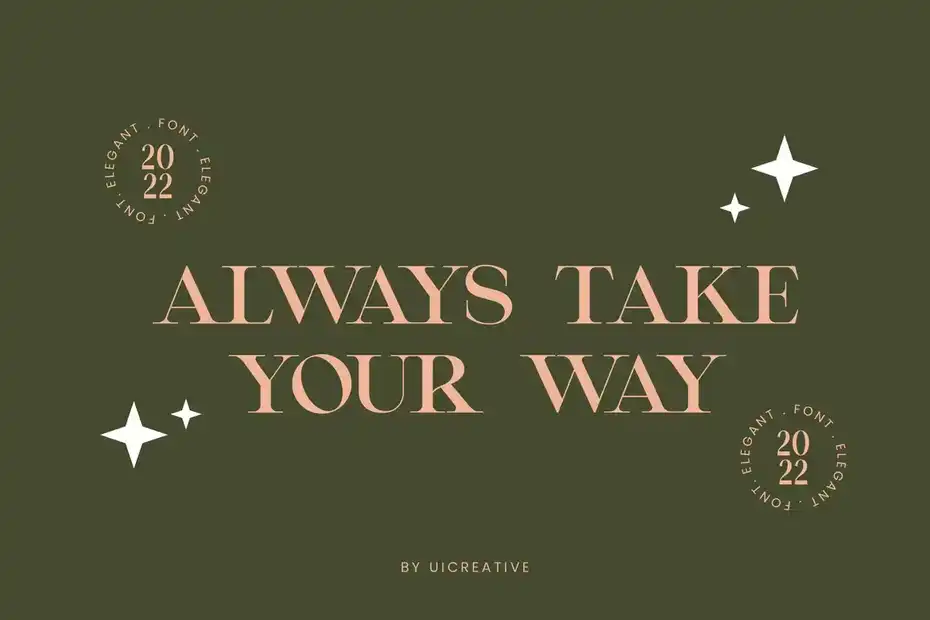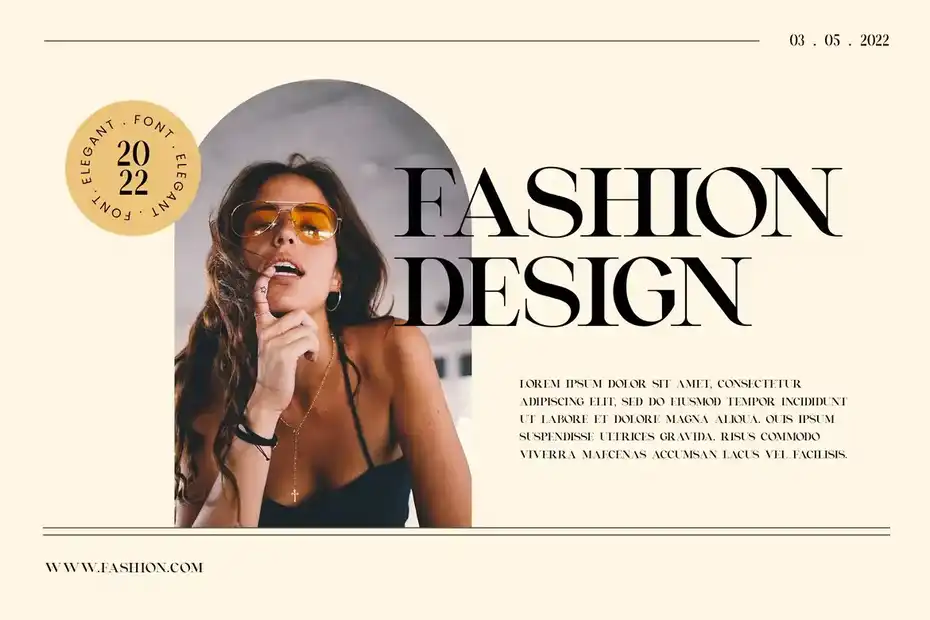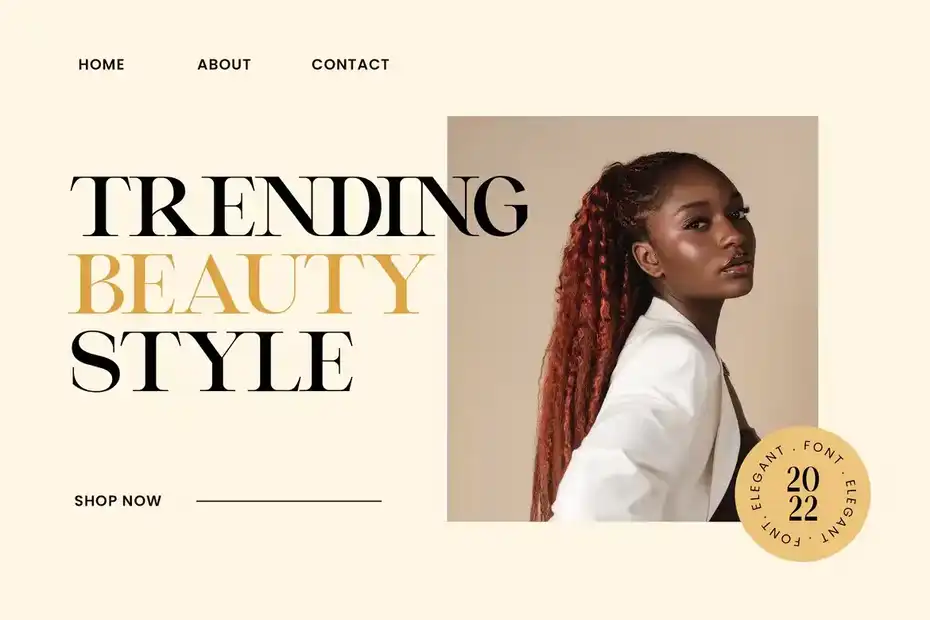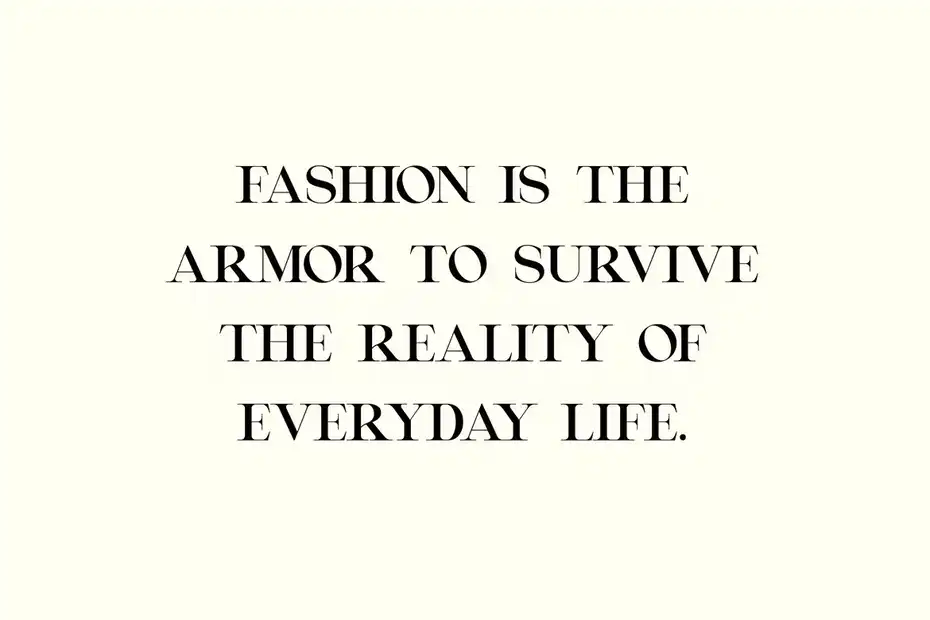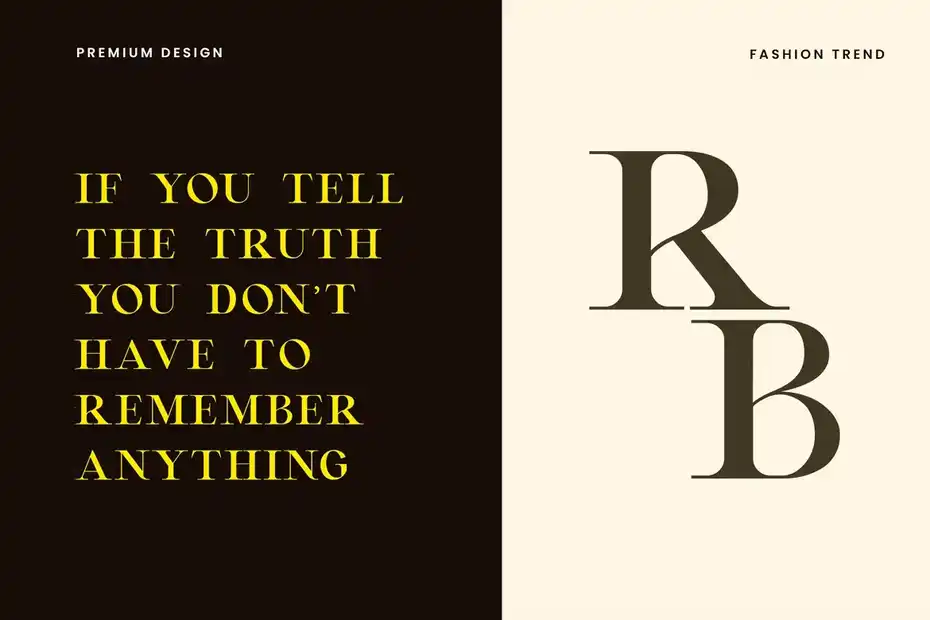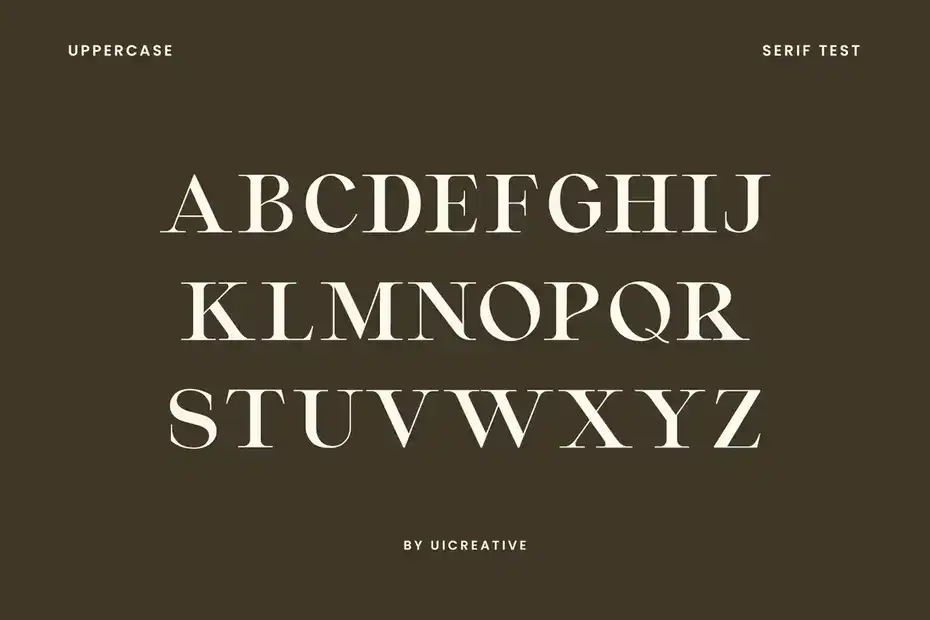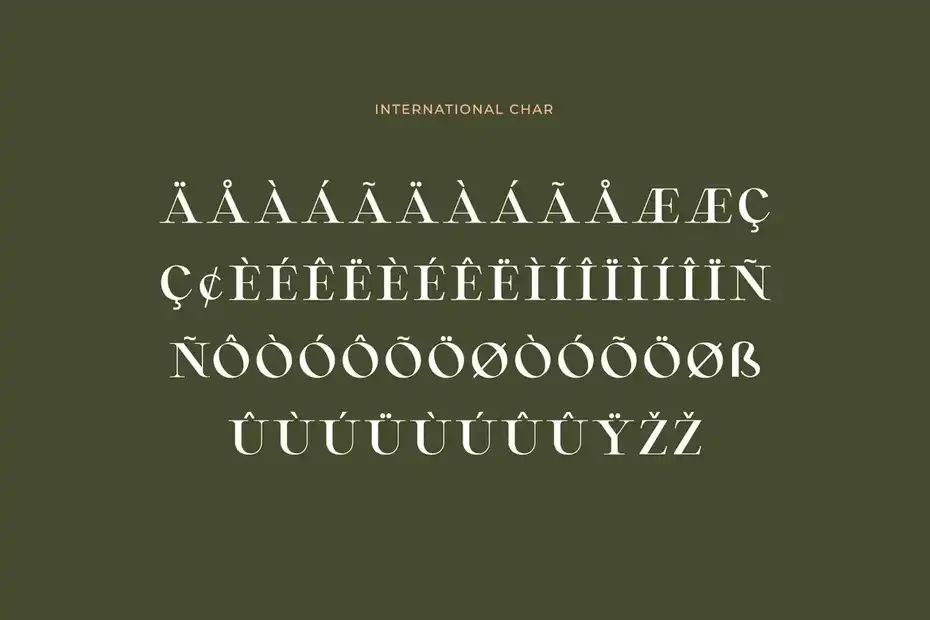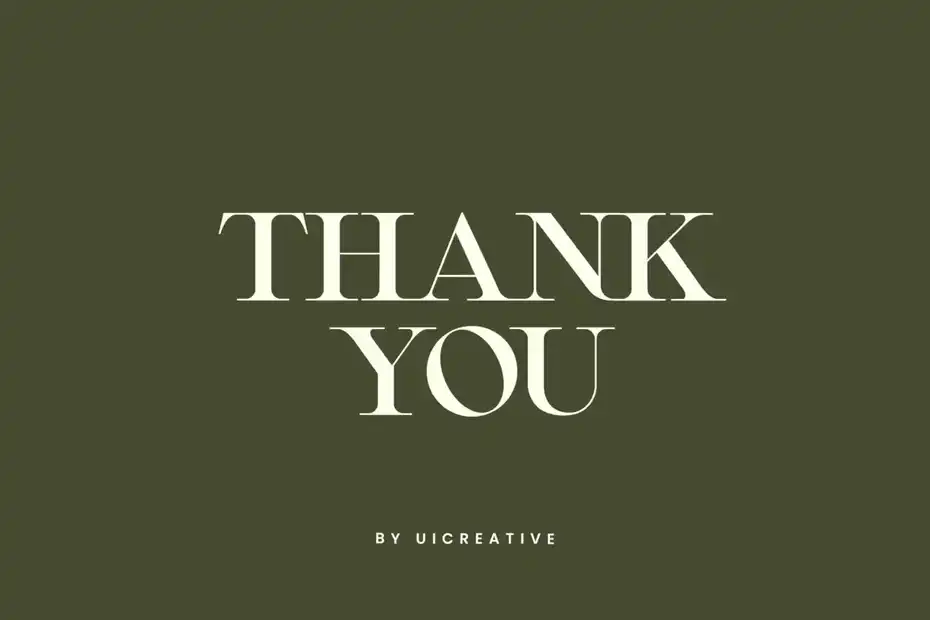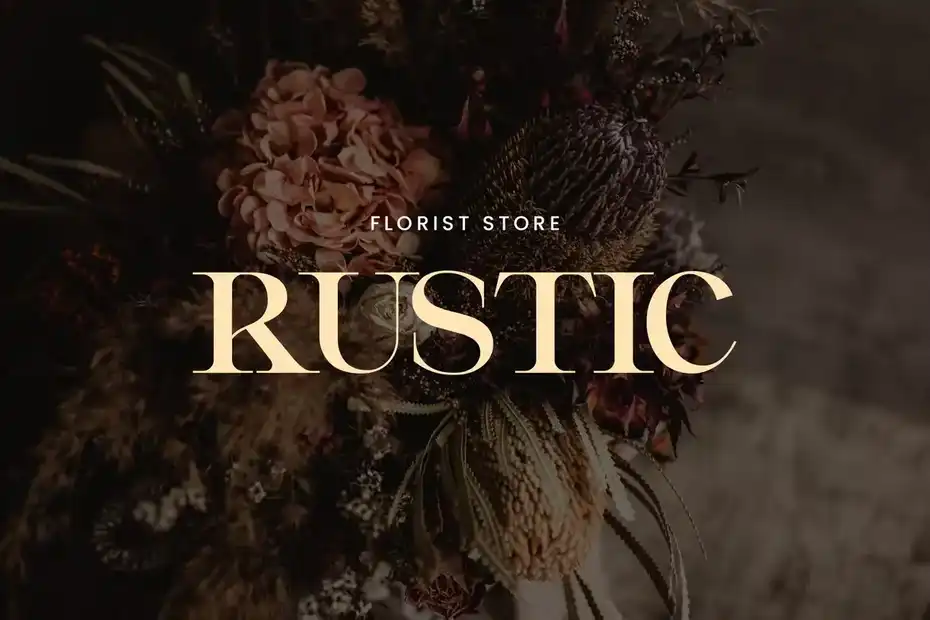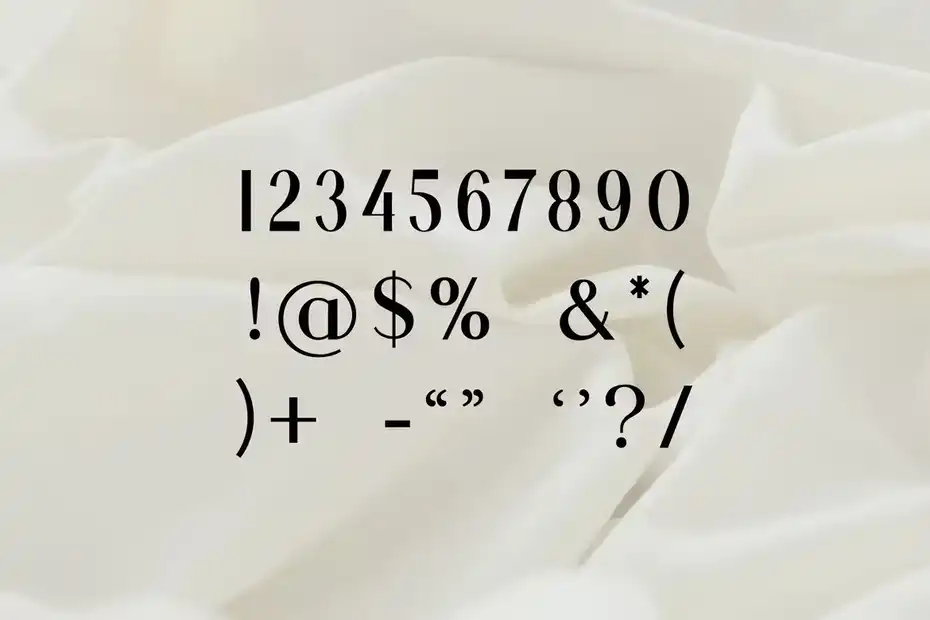
دانلود فونت انگلیسی Montvolca Elegant Serif Font
فونت انگلیسی Montvolca Elegant Serif Font : این فونت یک فونت مدرن Serif است که برای پروژه های مختلف مانند: امضا، برندینگ، لوگو، عروسی، نقل قول تایپوگرافی، جلد مجلات یا کتاب، سربرگ وب سایت، لباس، طراحی بسته بندی و غیره مناسب میباشد.
• عنوان مجموعه: Montvolca Elegant Serif Font
• سبک: Serif